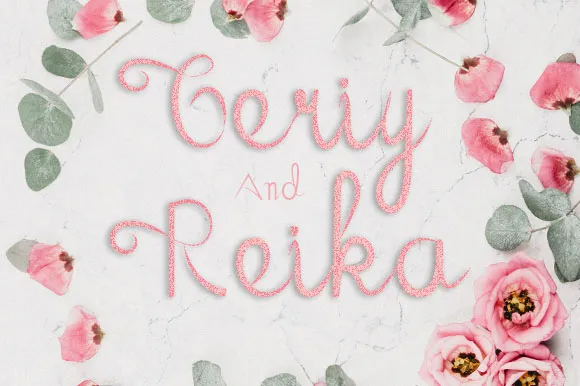
Geriy and Reika Font – Download Grátis
A fonte ‘Geriy and Reika’ é uma elegante e elegante escolha para qualquer projeto que exige um toque personalizado. Suas linhas suaves e detalhes refinados a tornam ideal para uso em cartões de casamento, cartões de agradecimento, cartazes de citações, cartões de lembrança, logotipos e cards de negócios. Seja você designer gráfico ou estilista, essa fonte oferece um toque sofisticado que destacará seu trabalho, tornando-o único e impecável. Sem dúvidas, é uma opção perfeita para qualquer projeto que exija um ar elegante e bem pensado. Não deixe de experimentar o ‘Geriy and Reika’ – ele certamente fará sua marca mais atraente.